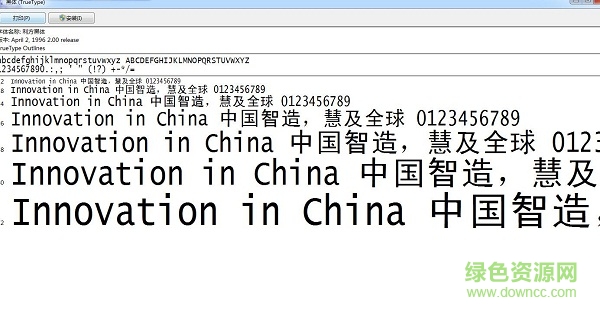
利方黑体字体
rs_hei 字体又叫利方黑体字体,这是一款非常朴素的实用性字体,干净简洁粗细相等,绿色资源网汇聚了大量的广告字体海报字体书法字体商业字体等一系列好看的字体,欢迎下载!
黑体字体特点
汉字的黑体是在现代印刷术传入东方后依据西文无衬线体中的黑体所创造的。由于汉字笔划多,小字的黑体清晰度较差,所以一开始主要用于文章标题,但随著制字技术的精进,已有许多适用于内文的黑体字型。
利方黑体字体